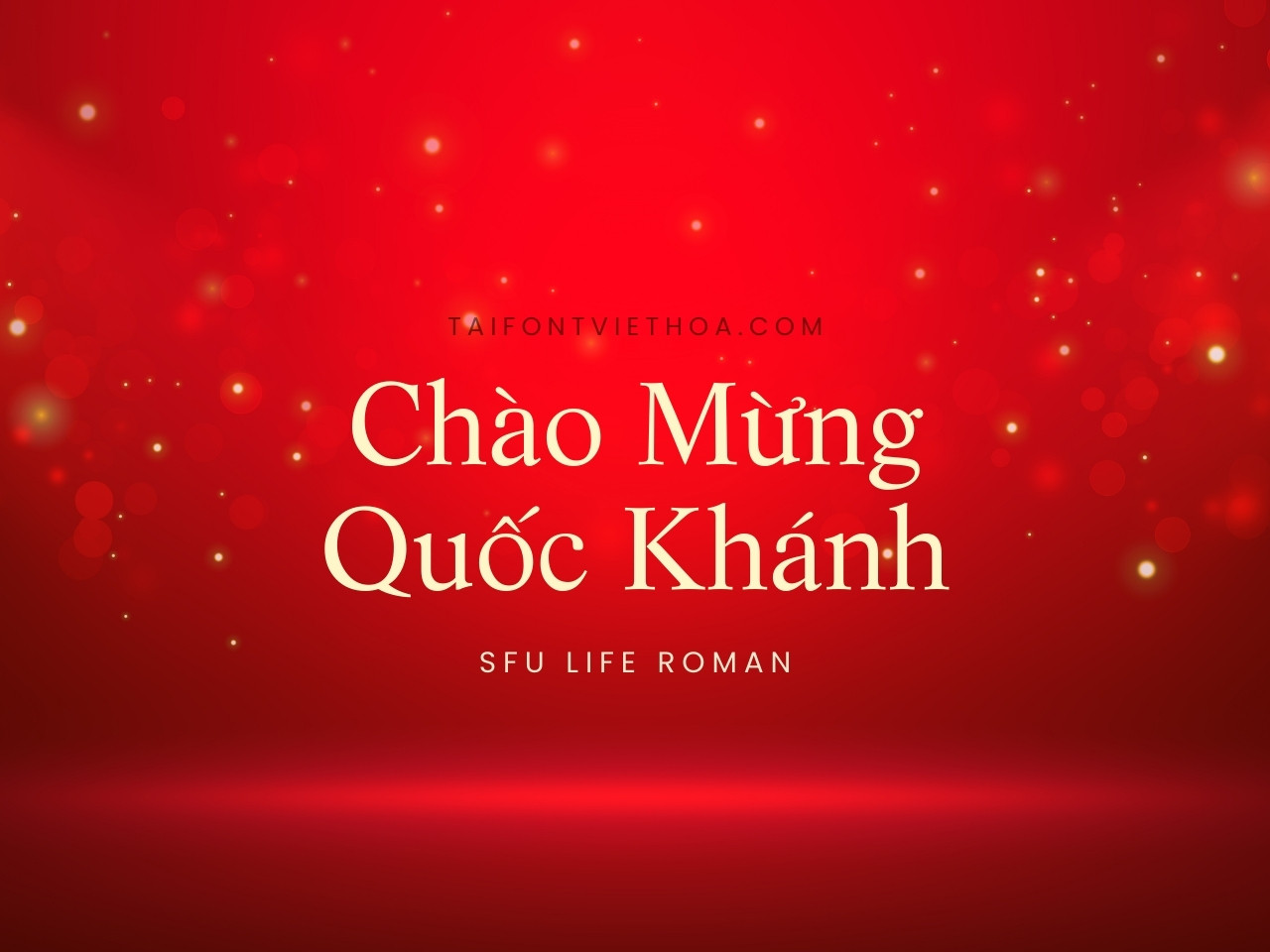
Giới thiệu về font SFU Life – Kiểu chữ serif thanh lịch, truyền thống và dễ tiếp cận
SFU Life là phiên bản Việt hóa của một font serif cổ điển, mang đậm tính truyền thống nhưng vẫn giữ được nét hiện đại trong thiết kế. Font được phát triển với mục tiêu tạo ra một kiểu chữ có khả năng truyền tải nội dung dài, dễ đọc và tạo cảm giác tin cậy. Với nguồn gốc từ một kiểu chữ dùng phổ biến trong sách, báo và tạp chí, SFU Life mang lại phong cách trang nhã, lịch sự và thân thiện với người đọc.
Phiên bản Việt hóa được thực hiện bởi nhóm SFU, đảm bảo hỗ trợ đầy đủ bộ dấu tiếng Việt, phục vụ trọn vẹn nhu cầu sử dụng cho các ngôn ngữ Latin mở rộng. Taifontviethoa.comđã chọn lọc và giới thiệu font SFU Life nhằm đáp ứng nhu cầu của cộng đồng thiết kế đang tìm kiếm một font serif dễ sử dụng, phù hợp với các ứng dụng thực tế từ giáo dục đến xuất bản và truyền thông thương hiệu.
Đặc điểm thiết kế cổ điển và ứng dụng đa lĩnh vực của SFU Life
Font SFU Life có cấu trúc serif nhẹ nhàng, với nét chân chữ thanh mảnh, độ tương phản vừa phải và khoảng cách chữ được tối ưu để tăng khả năng đọc. Thiết kế này mang lại hiệu ứng thị giác dễ chịu trong cả khối văn bản dài lẫn khi dùng làm tiêu đề trang trọng. Những đặc điểm này khiến font trở thành lựa chọn an toàn và hiệu quả cho nhiều lĩnh vực thiết kế chuyên nghiệp.
Ứng dụng lý tưởng: sách giáo khoa, tài liệu học thuật, bài báo, tạp chí in ấn, thiết kế logo cao cấp, bộ nhận diện thương hiệu truyền thống. Ngành nghề phù hợp: giáo dục, xuất bản, y tế, pháp lý, truyền thông, và các thương hiệu muốn thể hiện sự tin cậy, chuyên nghiệp và giá trị lâu dài.